ゴシック体
Noto Sans JP
WEBデザインで最も多く使われているフォントです。
シンプルで明るい印象のデザインで、長い文章や小さなサイズでも読みやすいのが特徴です。
英文でも読みやすさを損なわないため、スタイリッシュからオーソドックスなデザインまで幅広く使える万能フォントです。
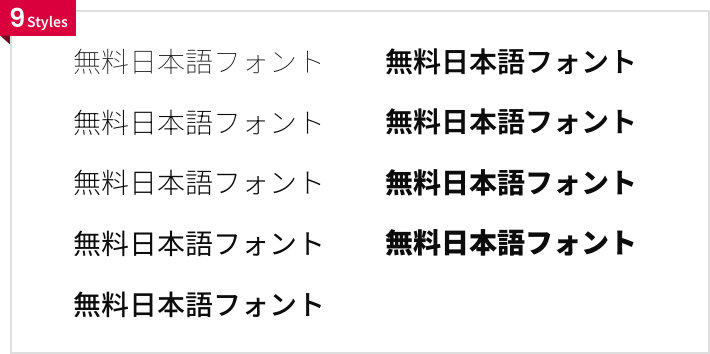
Sawarabi Gothic(さわらびゴシック)
オーソドックスなNoto Sans JPよりもやわらかさを感じさせるフォントです。
シンプルかつモダンなデザインで、ユーザーに信頼感や安心感を与えたい時におすすめです。
M PLUS 1
汎用性が高く、Noto Sans JPと同様によく使われているフォントです。
シンプルなので、様々なジャンルのデザインにマッチする柔軟性があります。
特に、ユーザーに対して直接的なメッセージを伝えたい場合や、情報を重視するデザインにおすすめです。
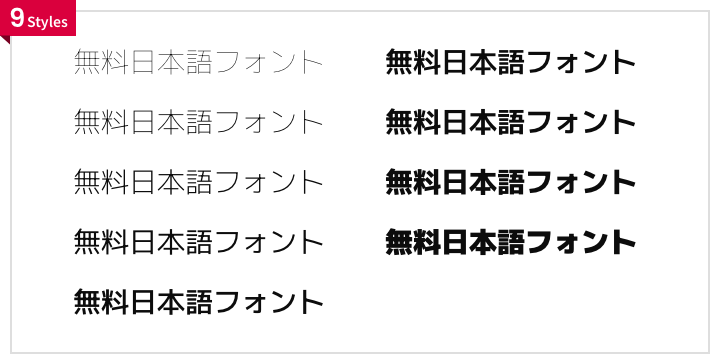
Zen Kaku Gothic New(ZEN角ゴシック)
シャープで角ばった形状が特徴的なフォントです。
文字の間隔やバランスに配慮されていて、現代的でクリーンな印象をあたえます。
シンプルでモダンなデザインにしたい時におすすめです。
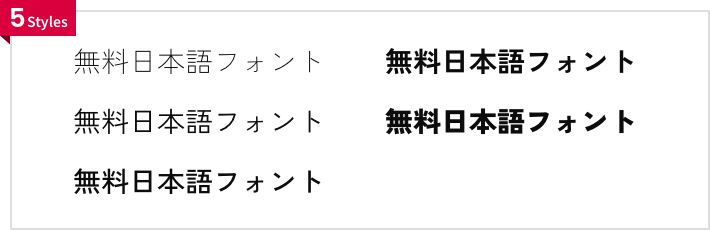
Kosugi(小杉)
モトヤ社によってデザインされたフォントです。
情報伝達の正確さと優れたデザイン性を併せ持ち、どのような場面にも馴染みます。
明朝体
Noto Serif JP
明朝体で最も多く使われているフォントです。
日本語を美しく魅せてくれるため、WEBサイトやポスター、書籍などで幅広く利用されています。
高級感や信頼感を出したい時におすすめです。
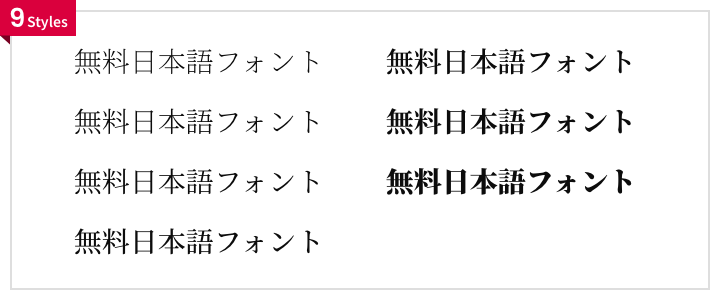
Sawarabi Mincho(さわらび明朝)
さわらびゴシックと同様に読みやすく、長文にも向いているフォントです。丸みのあるやわらかいタッチが特徴で、程よい太さなので安定感があります。
女性らしいデザインや、やわらかい印象を与えたい時におすすめです。
Shippori Mincho(しっぽり明朝)
見出しから本文まで幅広く使用できるフォントです。
なめらかで上品なタッチが特徴的で、縦書きでも横書きでも美しく見栄えします。
スタイリッシュで信頼感のある印象を与えたい時におすすめです。
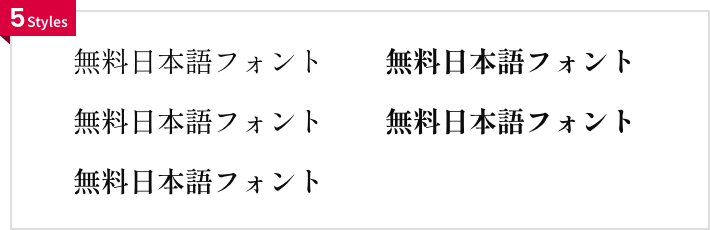
Zen Old Mincho(ZENオールド明朝)
レトロな雰囲気がありながら、読みやすいフォントです。
ひらがなにすると毛筆の流れるようなやわらかさを感じます。
誠実さや古風な印象を与えたい時におすすめです。
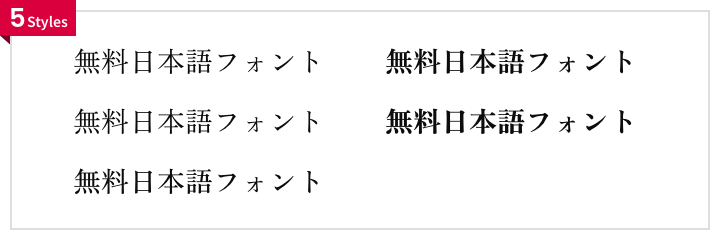
Hina Mincho(ひな明朝)
名前の通り、人形をイメージしてデザインされた古風な印象のフォントです。
品があり、丸みをおびた形状で優しい雰囲気があります。
伝統感を伝えたい場合や、やわらかい印象を与えたい時におすすめです。
丸ゴシック体
Kiwi Maru(キウイ丸)
手書きのような丸みのある、個性的なフォントです。
可読性が高く、ナチュラルで親しみやすい雰囲気があります。
子供向けのデザインやカジュアルな印象を与えたい時におすすめです。
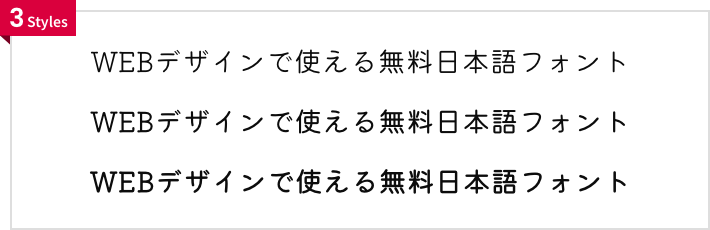
Kosugi Maru(小杉丸)
小杉と同じモトヤ社によってデザインされたフォントです。
直線が多く、スタイリッシュな印象の中にも親しみのある雰囲気があります。
Zen Maru Gothic
丸ゴシックの中でもウエイトが多く、どこか懐かしさを感じさせるフォントです。
深い丸みがあり、優しくナチュラルな雰囲気があります。
安心感を演出しつつ信頼性も保ちたいときにおすすめです。
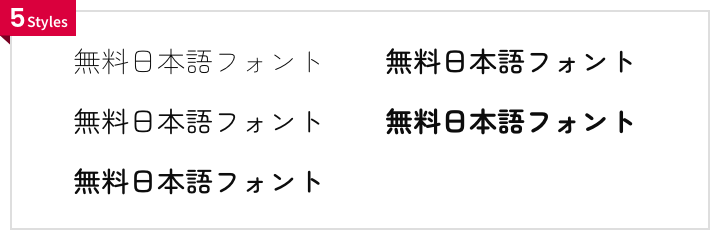
Kaisei Opti(解星オプティ)
「はね」や「はらい」に丸いドットがデザインされた個性的なフォントです。
個性的なわりに可読性が高く、モダンでかわいい雰囲気があります。
親しみを与えたい時やかわいいデザインをしたいときにおすすめです。
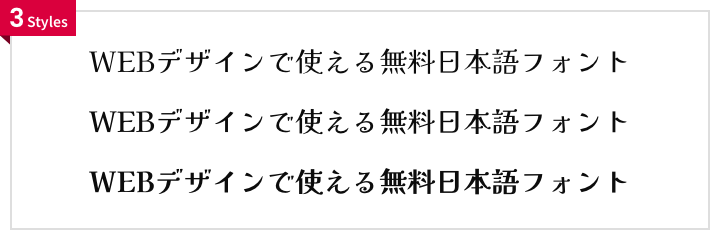
Zen Kurenaido(ZEN紅道)
ボールペンで書いたような手書き風フォントです。
可読性も優れており、手作り感と読みやすさを兼ね揃えています。
親しみのあるデザインや、少しくだけた印象を与えたいときにおすすめです。
Klee One(クレーワン)
細い鉛筆やボールペンで書いたような手書き風フォントです。
教科書体のような、優しく落ち着いた雰囲気があります。
女性らしさを表現したいときや、高級感を出したいときにおすすめです。
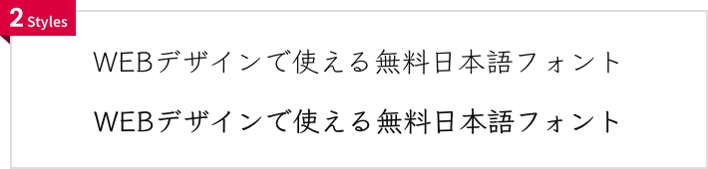
Yomogi
かわいらしさが溢れる手書き風フォントです。
極細の字画が特徴的でポップな雰囲気があります。
子供向けのデザインをしたいときや、かわいい印象を与えたい時におすすめです。
Mochiy Pop One
線に太さがあり、エネルギッシュな印象のフォントです。
ポップな雰囲気で力強さがあるため、バナー内のキャッチコピーにおすすめです。
Yuji syuku
毛筆文字がベースとなっている手書き風フォントです。
バナーなどで、和風な雰囲気を与えたい時におすすめです。